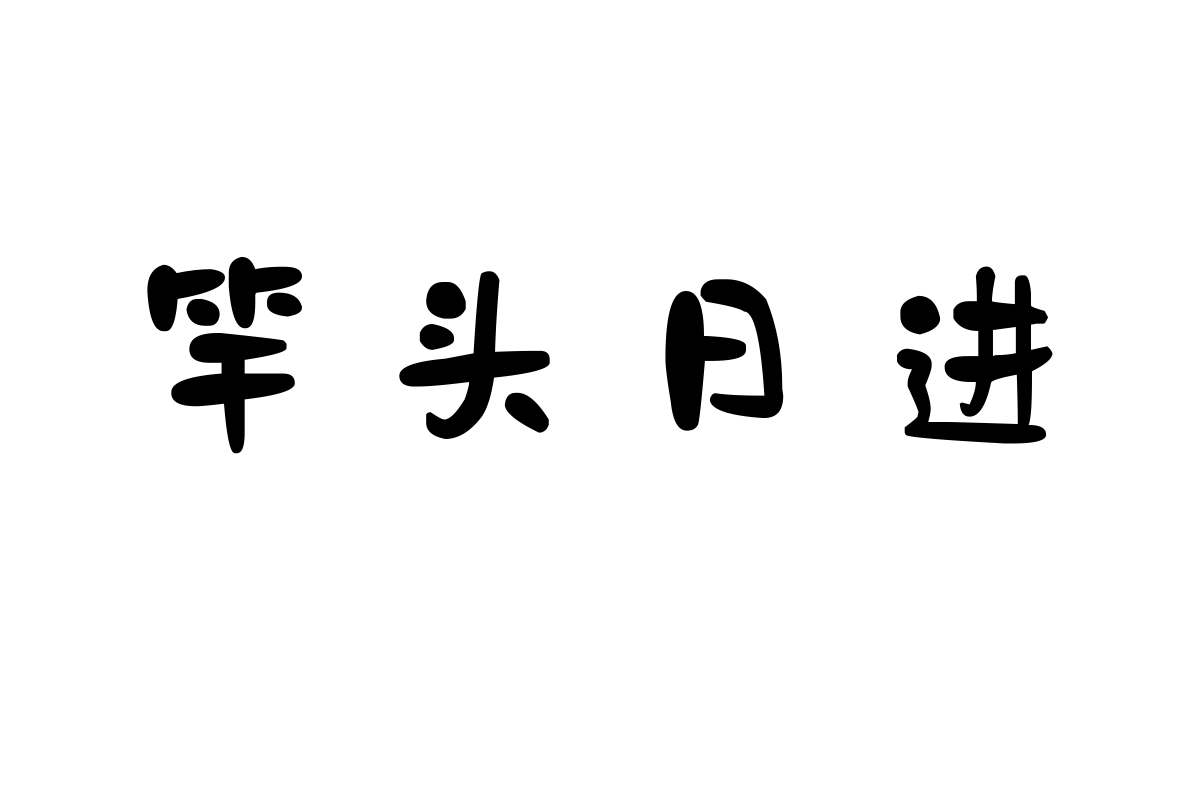
也字工厂小石头体是一款现代简约风格的字体,具有独特的字形结构和笔画风格。这款字体的特点是笔画流畅自然,结构紧凑有序,给人一种简洁明快的感觉。同时,也字工厂小石头体的笔画粗细变化丰富,既有粗犷的线条,又有细腻的笔触,使得整个字体既有力度又不失柔美。
这款字体适用于各种需要表达现代、简约风格的设计场景,如海报、广告、网页、包装等。无论是用于标题、正文还是装饰元素,都能有效提升设计的视觉冲击力和美感。